Fontes gratuitas para logotipos | +50 fontes e tipos de letra
A escolha de fontes para logotipos é um processo bastante complexo, mas também muito importante, portanto, não pode ser feito de forma leviana. Se estiver se perguntando quais são as melhores fontes para logotipos, estamos aqui para ajudar.
1. Como escolher o tipo de letra para logotipos:
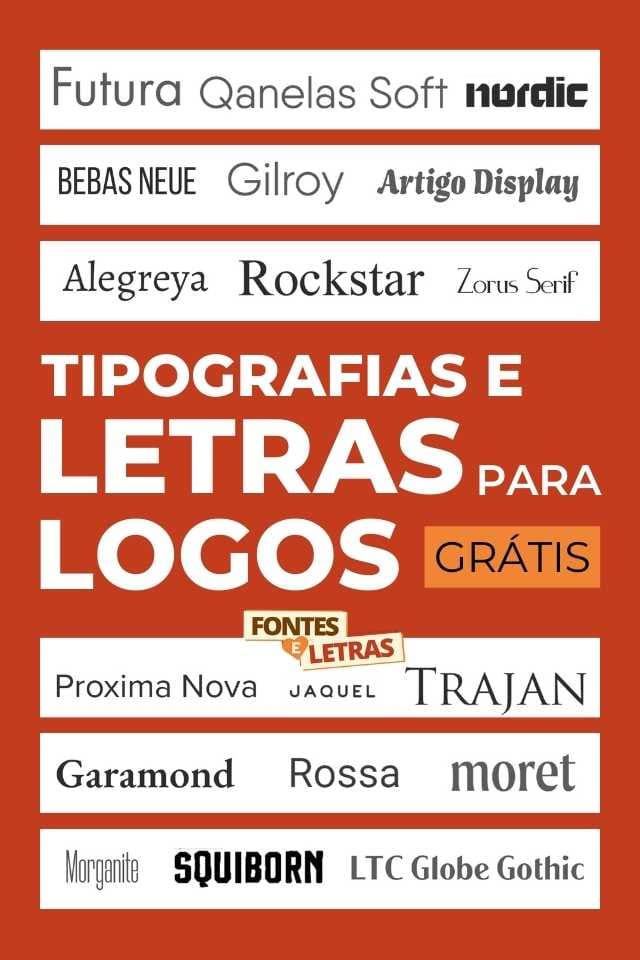
A primeira coisa que você precisa fazer para encontrar as fontes corretas para logotipos de sua marca ou empresa é ter clareza sobre os pontos a seguir e seguir as orientações.
# Não opte pelo comum
Não use as fontes de logotipo que milhões de pessoas já usam, você pode encontrar muitas opções em conversores de fontes. Há milhares de opções gratuitas que podem ajudá-lo a criar uma ótima imagem para sua marca.
A vantagem é que você pode visualizar o resultado em diferentes fontes de logotipo para ver qual se adapta melhor à sua empresa.
# Optar por fontes atemporais
Muitas fontes para logotipos têm um grande boom, mas depois entram em declínio e perdem seu impacto. É melhor considerar fontes atemporais que nunca saem de moda.
Não siga o que a maioria das pessoas está fazendo; concentre-se em garantir que o seu logotipo tenha fontes que prevaleçam para que você não tenha que ficar mudando e perca a formalidade.
# Foco na legibilidade
Esse ponto parece óbvio, mas às vezes se perde de vista durante o processo de escolha da fonte para o logotipo. Sempre priorize a legibilidade em vez do estilo ou da originalidade.
Muitas vezes são escolhidas fontes muito atraentes e ornamentadas, mas elas são ineficazes porque são difíceis de decifrar.
# Preste atenção à distribuição das fontes
Se for escolher duas fontes (não recomendamos escolher mais), você deve cuidar do espaço entre os caracteres. Muito espaço pode fazer com que seu logotipo pareça desarticulado e o contrário pode fazer com que ele pareça muito ocupado. Encontre um equilíbrio.
Ele também procura garantir que as duas fontes sejam compatíveis, que não sejam muito semelhantes, mas que se complementem harmoniosamente.
2. Fontes gratuitas mais populares para logotipos
Há alguns tipos de letras para logotipos que são amplamente usados por suas características, simplicidade e formas. Entre eles estão os seguintes:
- Fontes com serifa: têm pequenas linhas verticais em cada traço; são um dos clássicos e há um grande número delas.
- Sanserif: não possuem serifas e tendem a ter um design menos clássico e mais moderno, visando à novidade, mas sem deixar de lado a limpeza.
- Letras modernas: são fontes versáteis e inovadoras, fáceis de ler e geralmente têm bordas arredondadas, o que dá aos logotipos uma aparência elegante.
3. As 50 melhores fontes de logotipo gratuitas
Precisa de ideias sobre quais fontes são ideais? Não precisa procurar mais. Aqui está uma lista das 50 melhores fontes gratuitas para logotipos.
1. Squiborn
2. Futura
3. Morganite
4. Jaquel
5. Nordic
6. Alegreya
7. Gilroy
8. Garamond
9. Trajan
10. Qanelas soft
11. Moret
12. LTC Globe Ghotic
13. Artigo Display
14. Proxima Nova
15. Rockstar
16. Bebas Neue
17. Insomniac
18. Rossa
19. Steady
20. Zorus Serif
21. Akura Popo
22. Norwester
23. Bennet
24. Harabara
25. Helvetica
26. Berliner
27. Suprema
28. Modesto
29. Mosk
30. Rockwell
31. Aileron
32. Bely
33. Frutiger
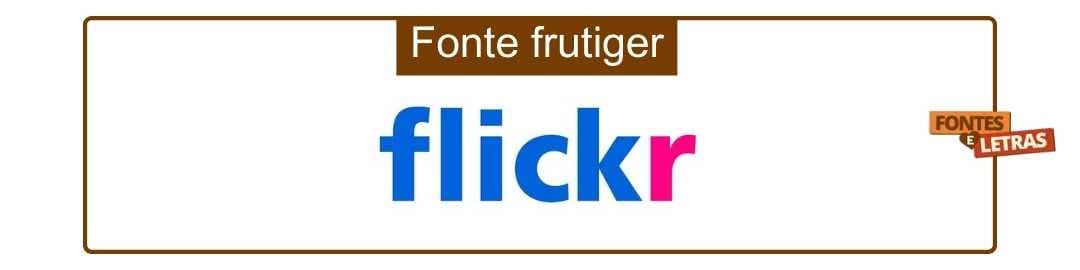
34. Klavika
35. Gruppo
36. Horizon
37. Mentone
38. Big Caslon
39. Bw Surco
40. Nova Square
41. Coves
42. Sassoon
43. Maxwell
44. Bodoni
45. Tondo
46. Fenix
47. Bambusa Pro
48. Didot
49. Aventura
50. Butler
4. A importância dos tipos de letra para os logotipos
As tipografias para logotipos são muito importantes, principalmente porque permitem que os logotipos sejam legíveis e claros e ajudam a realmente comunicar o que se deseja com a marca em questão.
Pergunte a si mesmo… o que você quer comunicar com seu logotipo? Começando com três elementos principais:
- Contexto da sua marca: em que mídia ou mídias você usará o seu logotipo?
- A tipografia de seu logotipo será acompanhada de símbolos ou outros elementos? Em caso afirmativo, quais?
- O que você quer que aconteça com seu logotipo ao longo do tempo?
5. Como obter as melhores fontes gratuitas para logotipos
Há inúmeras fontes de logotipo gratuitas, com diferentes tendências ou designs, como minimalista ou moderno, o importante é que você dedique tempo suficiente para explorar as opções.